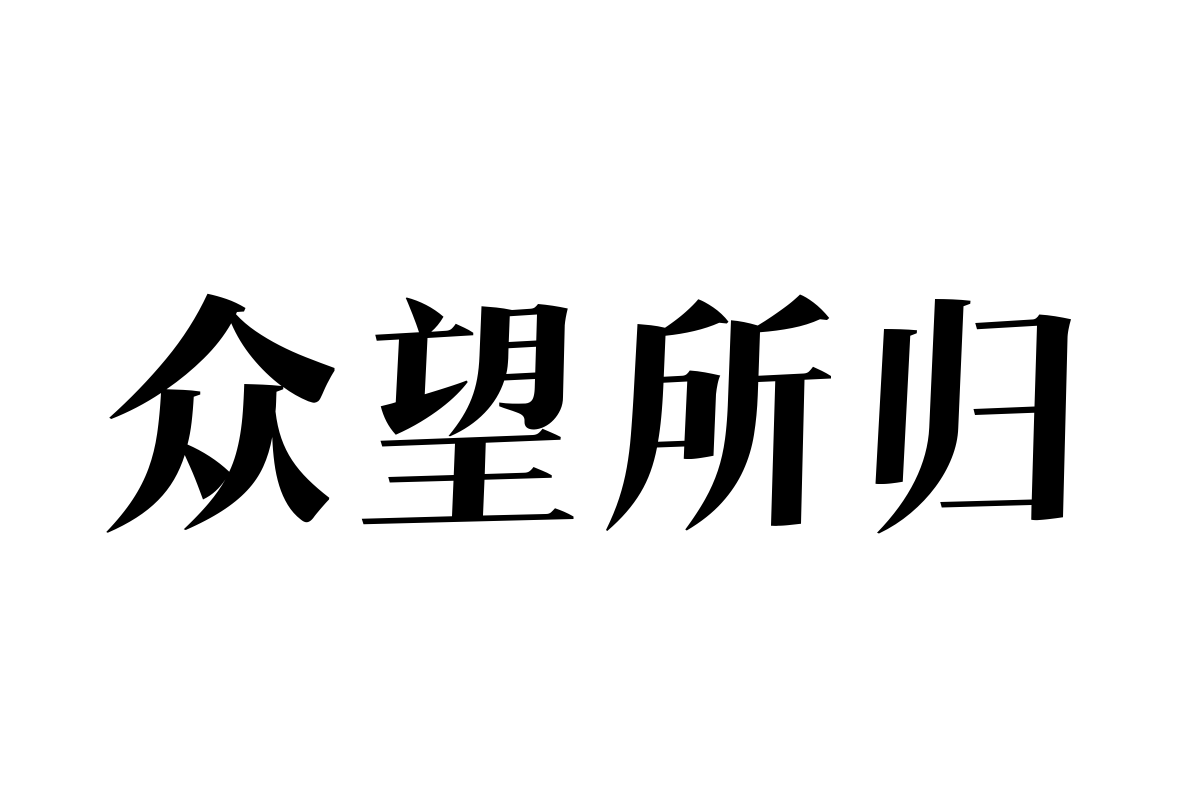
汉仪瑞意宋I_80W是一款现代的中文字体,具有简洁而优雅的外观。这款字体的设计灵感来源于中国传统文化中的吉祥元素,如云纹、龙纹等,使得整体风格既庄重又不失灵动。
该字体的特点包括:
1. 字形优美:汉仪瑞意宋I_80W采用了独特的字形结构,使得整个字体看起来既规整又富有变化。每个字符都经过精心设计,确保在视觉上呈现出和谐统一的效果。
2. 笔画流畅:该字体的笔画线条流畅自然,给人一种轻松愉悦的感觉。无论是书写还是阅读,都能让人感受到一种舒适和愉悦的体验。
3. 易于辨识:汉仪瑞意宋I_80W的字形独特,使得其在众多字体中脱颖而出。这使得它在各种场景下都能快速被识别和记忆,提高了使用效率。
4. 适用范围广泛:无论是用于印刷品、广告设计、网页制作还是其他应用场景,汉仪瑞意宋I_80W都能展现出其独特的魅力。它能够满足不同用户的需求,提高整体视觉效果。
总之,汉仪瑞意宋I_80W是一款非常实用的中文字体,无论是在商业设计还是个人使用中都能发挥出良好的效果。